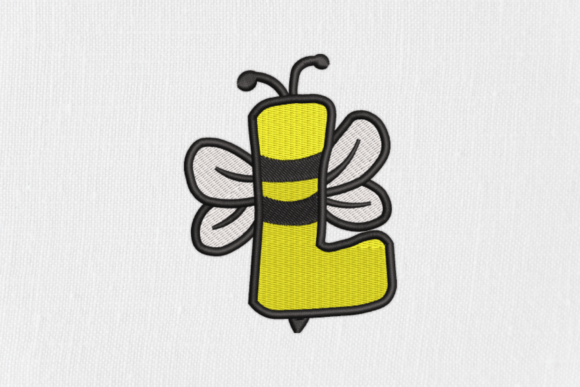
Letter L Bee Monograms
Ulasan Lengkap: Letter L Bee Monograms – Monograma de Abelha que Encanta
Se você busca um toque lúdico e ao mesmo tempo elegante para seus projetos de bordado, o Letter L Bee Monogram é a escolha perfeita. Essa criação única combina a simplicidade da letra L com a energia vibrante de uma abelha, resultando em um design que literalmente faz seu artesanato “zum‑zum” de criatividade.
Por que este monograma se destaca?
- Fusão artística impecável: A letra L foi transformada em uma abelhinha detalhada, unindo tipografia e ilustração de forma harmoniosa.
- Versatilidade de uso: Ideal para toalhas, almofadas, camisetas, bolsas e até quadros decorativos.
- Qualidade profissional: Desenvolvido por um designer premiado, garante linhas nítidas e pontos bem definidos em qualquer tipo de tecido.
- Significado simbólico: Abelha representa trabalho, comunidade e doçura – valores que dão mais personalidade ao seu bordado.
Experiência de uso
Ao aplicar o Letter L Bee Monogram, você sente imediatamente a diferença: os detalhes das asas e o corpete da abelha ficam nítidos mesmo em tecidos leves, enquanto a curvatura da letra L mantém a legibilidade. O resultado é um bordado que parece “viver”, atraindo olhares e elogios.
Dicas para potencializar o efeito “buzz”
- Combine com linhas em tons de amarelo e preto para realçar a identidade da abelha.
- Use fundos neutros (branco, bege ou cinza) para deixar o monograma em destaque.
- Adicione pequenas flores ou folhas ao redor da letra para criar um cenário natural.
- Experimente diferentes pontos (ponto cheio, ponto francês) para variar a textura.
Em resumo, o Letter L Bee Monograms não é apenas um simples monograma; é uma experiência criativa que traz personalidade, estilo e um toque de natureza ao seu artesanato. Dê à sua próxima peça de bordado o som da criatividade – deixe-a zum‑zum com este design exclusivo!